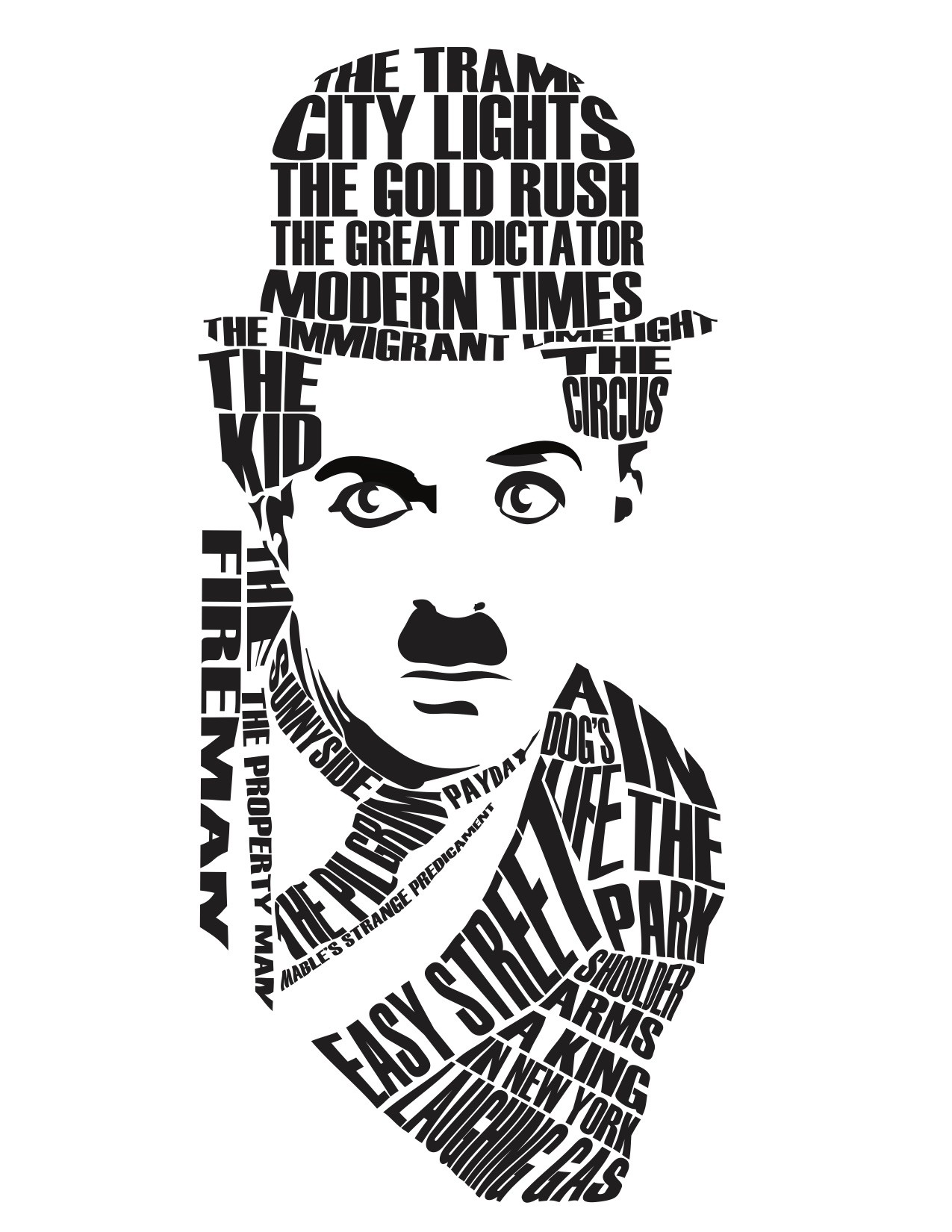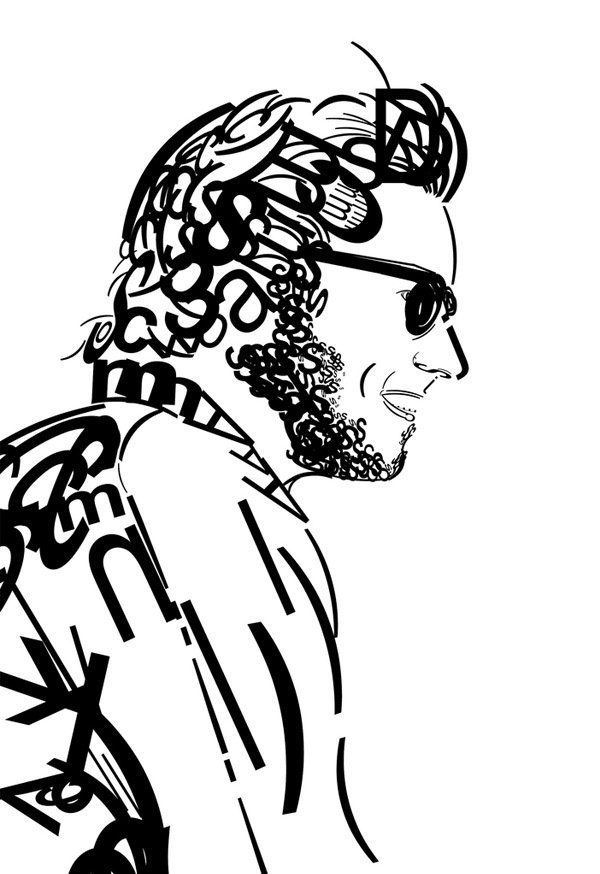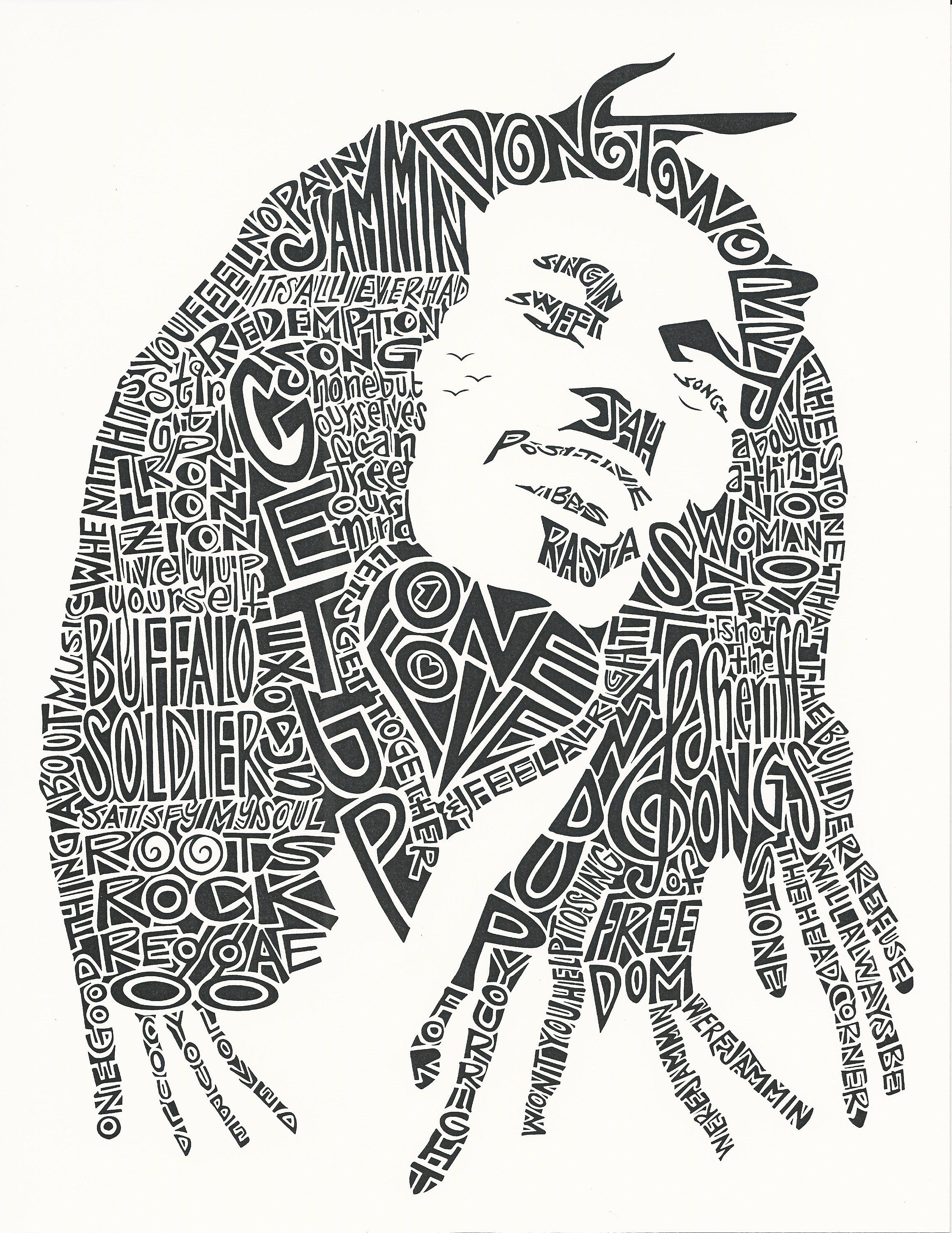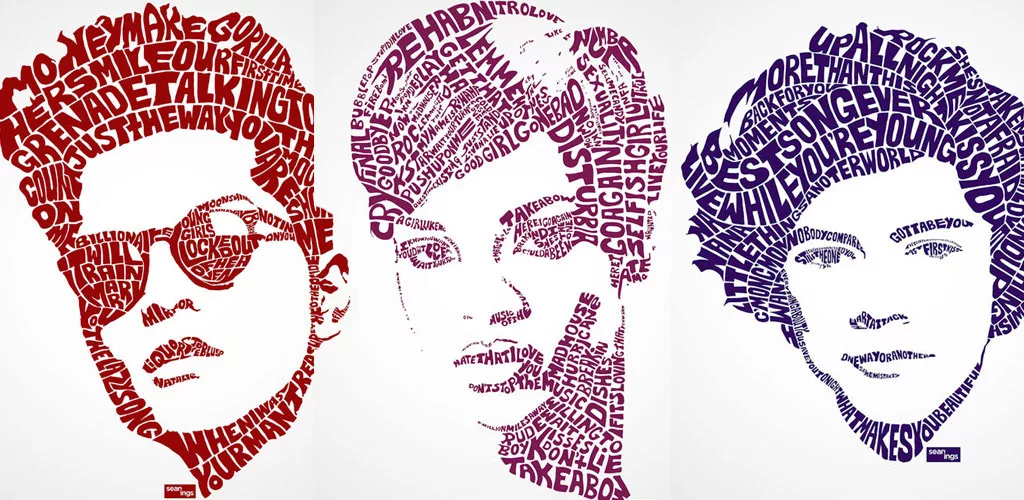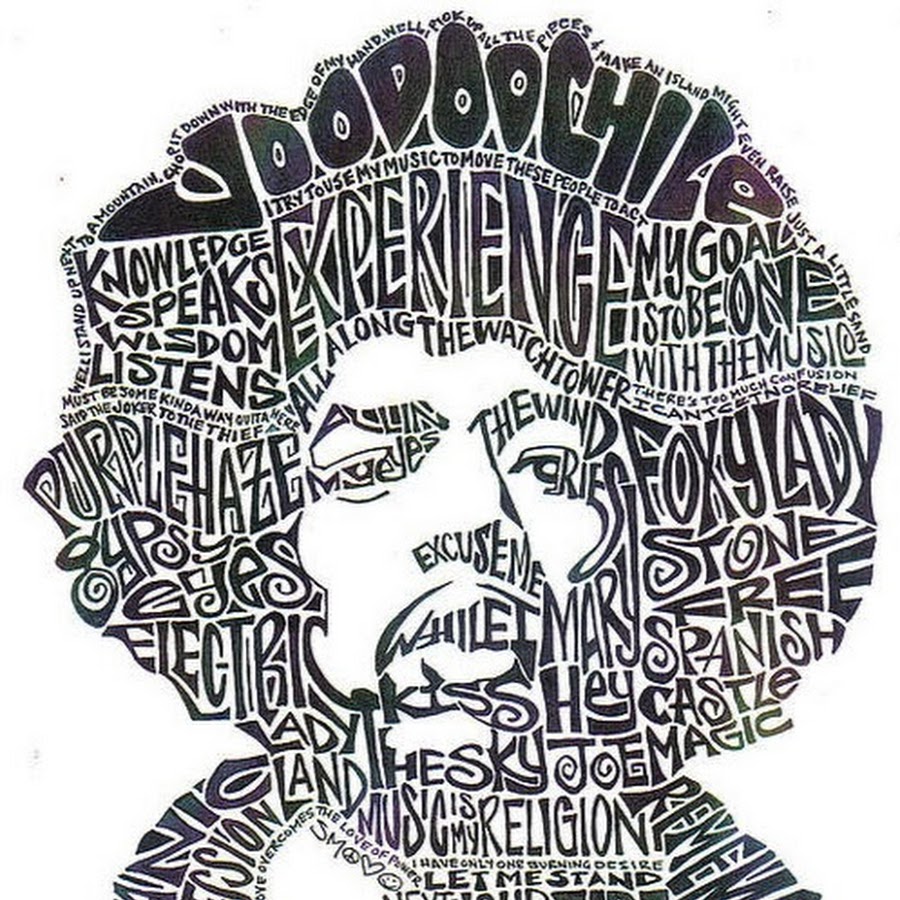
Суперлегкий типографический портрет
В этом уроке я покажу вам, как создать действительно интересный и удобный типографский портрет в Photoshop. Мы будем использовать фильтр Displace и некоторые режимы наложения для достижения эффекта. Весь процесс довольно прост, но может занять некоторое время на добавление текста и элементов, но как только вы сделаете это, все пойдет гораздо быстрее.
Шаг 1
Откройте Photoshop и создайте новый документ. Я использовал размер 2560×1440 пикселей. Затем импортируйте Ваше фото, я же использую портрет Джона Арлингтона. Фото у меня на белом фоне, так что убираем фон.
Шаг 2
Дублируем слой и переходим к Image>Adjustment>Desaturate .Вы получите черно-белую фотографию. Добавьте белый фон. После этого сохраните файл, он должен быть PSD, в противном случае не будет работать фильтр Displace.
Шаг 3
С Horizontal Type Tool (T) создаем текстовые поля и начинаем добавлять тексты.
Кроме того, я сделал несколько ключевых слов намного больше, выделил некоторые слова (Photoshop Tutorials, Illustrator, Inspiration…). Также поменял начертание, выравнивание текста и размеры. Подсказка: я использовал Garamond, думаю, с засечками шрифты выглядят гораздо лучше для этого эффекта.
Шаг 4
Для каждого слоя сделайте Layer>Layer Style>Drop Shadow. Используйте настройки Multiply для Blend Mode , black для color, 90º для Angle and 5 pixels для Distance, Spread и Size .
Группируем все слои и дублируем группу. Далее сливаем группу Layer>Merge Group и накладываем фильтр Filter>Blur>Gaussian Blur . Используем 10 pixels для Radius . Оставляем этот размытый слой Добавляем некоторую глубину в текст с помощью тени.
Шаг 5
Выделите все слои текста и объединить их в один слой, только затем перейдите к Filter> Distort> Displace.
В появившемся окне выберите файл, который мы создали на шаге 2. Используйте настройки 15 для Horizontal и Vertical Scale; Tile для Displacement Map и Repeat Edge Pixels для Undefined Areas.
Шаг 6
Переместите слой с фото поверх слоя белого текста и измените режим наложения на Light Burn.
Шаг 7
На фото слишком много деталей, идем в Filter>Noise>Dust & Scratches. Используем 7 pixels для Radius и 0 levels для Threshold.
Шаг 8
Сделайте маску текстового слоя так, чтобы остался текст только на фото.
Вы можете уменьшить немного насыщение и, как я уже говорил, вы можете добавить больше слоев текста и даже пробовать разные символы и формы.
Есть много способов создать этот эффект, этот, возможно, является самым простым, но вы должны быть очень осторожны, чтобы сделать все очень тонко, иначе эффект будет выглядеть не так круто, как мы ожидаем.
com – сайт дизайнераСегодня в уроке мы рассмотрим как сделать типографический портрет, используя один лишь Photoshop. Урок не сложный и у большинства он не должен вызвать трудностей. Приступим!
Откройте Photoshop и создайте новый документ. Я создал документ размером 2560×1440 пикселей. Затем импортируйте вашу фотографию. У меня было фото на белом фоне, но нам фон не нужен, поэтому – убираем его.
Дублируйте слой с фотографией и перейдите к Image> Adjustment> Desaturate . Вы получите черно-белую фотографию. Добавить белый фон. После этого сохраните файл, он должен быть PSD формата , иначе он не будет работать с Displace фильтром (это пригодиться нам в будущем).
С помощью инструмента Horizontal Type Tool (T) создадим текстовые фрагменты. Идея состоит в том, чтобы составить текст таким образом, чтобы они оставались легкочитаемыми, или, по крайней мере, разборчивым, поэтому изменяйте высоту строк, используйте наложение текста друг на друга.
Также сделайте некоторые ключевые слова намного больше, и жирней, как сделал я. Кроме того, можно сделать текст курсивом и обычным текстом. Совет: Я использовал шрифт Garamond для написания, я думаю, что шрифты с засечками для этого эффекта подходят больше.
Для каждого слоя текста, сделайте тень Layer> Layer Style> Drop Shadow . Используйте Multiply для режима наложения тени, а также черный цвет, 90° для угла и 5 пикселей для Distance, Spread и Size .
Кроме того, сгруппируйте все слои и продублируйте группу. Перейти к
Вы можете дублировать первоначально текст еще несколько раз и переместить его немного выше и левей, это добавит еще больше глубины.
Выберите все текстовые слои и слейте их в один слой, затем перейдите к Filter> Distort> Displace
Карта смещения будет искажать слой на основе фотографии, которую мы использовали, темные тона опускают наш текст, а светлые поднимают.
Поставьте слой фотографии поверх белого текстового слоя, а затем измените режим смешивания для слоя фото на Linear Burn
Фотография имеет слишком много деталей, так что пойдем в Filter> Noise> Dust & Scratch . Установите значение 7 пикселей для Radius и 0 уровней для Threshold.
Маскируйте текстовый слой, так чтобы он не выходил за пределы фотографии.
Типографский портрет TheWorldIsTooSmall
Художник сделал оригинальную фотографию женщины и вписал в нее слова с помощью цифрового мастерства.
Я дарю тебе желание от Lupuscrystalus
Портрет Ван Томико из группы Do As Infinity . Художник тщательно выделил такие детали, как роза на пальцах певицы, и особенно акцентировал внимание на контрасте между тенями и ее профилем.
Обремененный Барак Обама от Dylanroscover